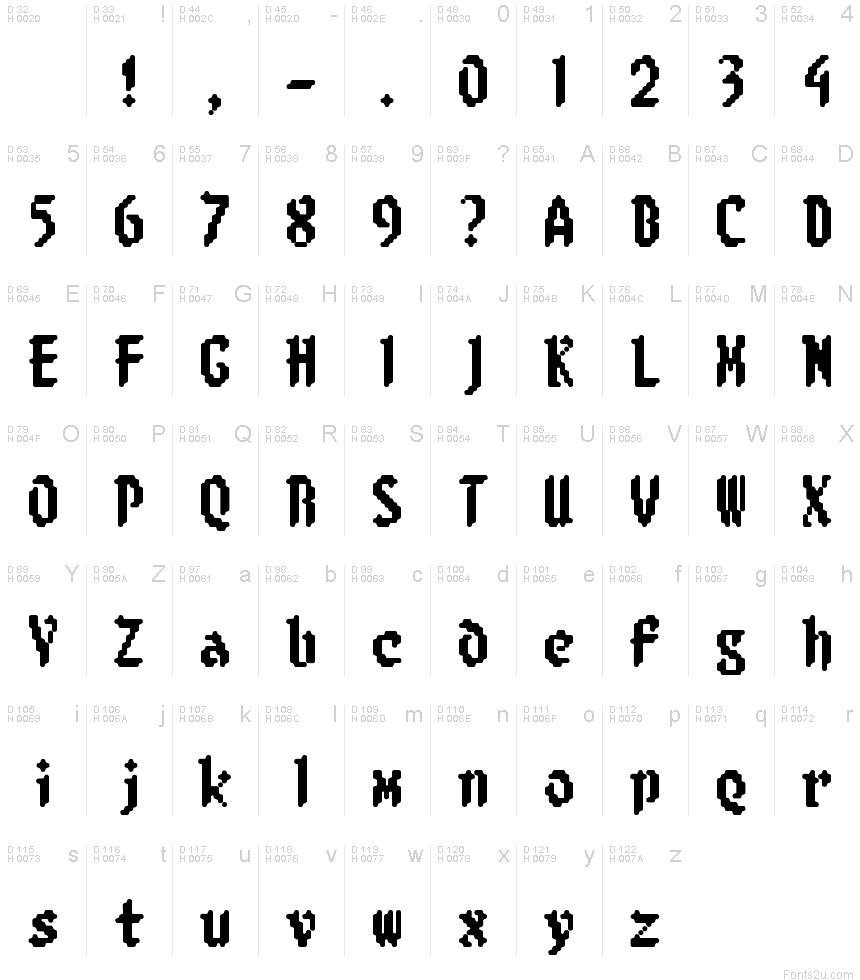
8-bit Limit R to wyrazisty, wąski krój pisma typu bitmap, przywołujący klimat retro klasycznych gier wideo. Jego pikselowe, kanciaste formy emanują odważnym, nostalgicznym charakterem, co czyni go idealnym wyborem dla projektów poszukujących unikalnego, inspirowanego stylem retro efektu wizualnego. Wąska budowa zapewnia kompaktowość i oszczędność miejsca, oferując wszechstronność w wielu zastosowaniach – od przyciągających wzrok nagłówków po wyraziste logotypy i identyfikacje wizualne. Ten wyróżniający się styl wzbogaci projekty wymagające dynamicznego, retro-futurystycznego sznytu, płynnie łącząc urok vintage ze współczesną wrażliwością.
Charakterystyczne cechy tego kroju sprawiają, że jest to przekonująca opcja dla projektantów chcących nadać swojej pracy urzekającą estetykę lo-fi. Jego ostre, kanciaste kształty i pikselowe tekstury tworzą odważną, przykuwającą uwagę obecność, która podniesie jakość zarówno projektów cyfrowych, jak i drukowanych.
8-bit Limit R (BRK)